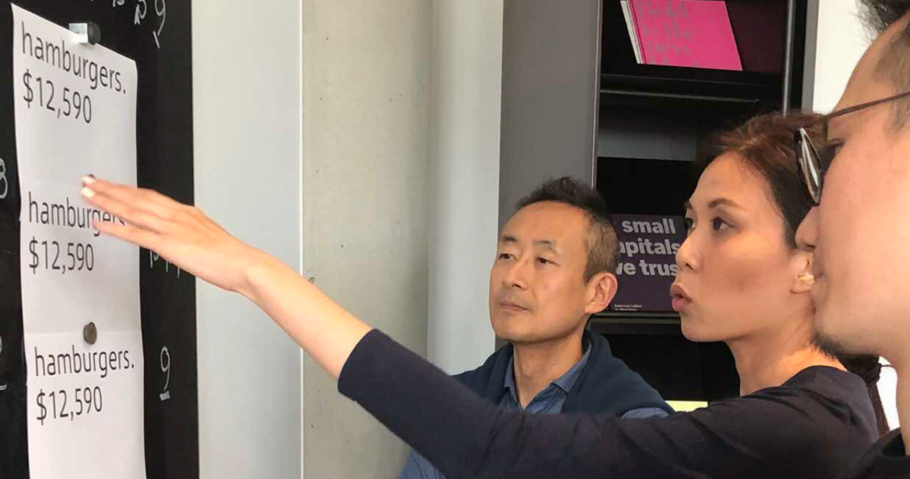
阿里巴巴集团的新字体赋能商家生态,让商业美而简单。
这套定制设计的 Alibaba Sans 字体家族将帮助其合作伙伴与客户提高品牌设计力。
挑战
阿里巴巴集团的企业品牌团队面临着各种设计挑战,因为在其创意团队、下属部门以及其庞大的数字合作伙伴和供应商生态系统中,一直使用着多个不同的开源字体。
随着业务快速增长,阿里巴巴越发需要一套统一、灵活、创新的字体家族,以保证设计师在能自由尝试的同时,又能严守品牌与知识产权规范。由于集团的核心业务是电商和零售,因此阿里巴巴字体不仅对字母有需求,对数字和货币符号的要求也极高。而更大的挑战是,阿里巴巴还希望在不断扩大的市场进行品牌营销活动时能轻松地与同事、合伙伴与客户分享这款品牌字体。
解决方案
Monotype 与阿里巴巴的设计团队成员通过真正的深层协作,组织了一系列为期多天的设计研讨会,聚焦于梳理新字体的设计理念,并讨论如何将阿里巴巴的企业个性融入其中。
Monotype 的设计团队由字体总监小林章先生领导。面对阿里巴巴集团的难题,他从绘制数字和货币符号入手,优先设计了电商业务最为重要的核心部分。团队从零开始,绘制数字和字母,创作出了 Alibaba Sans,其中还包括了造型独特的小写字母 a。这套字体不仅要赏心悦目,在粗字重下亦是如此;而且要能清晰易认,无论在各种设备和地点、无论字号大小——从横跨多栋写字楼的显示屏幕,到公司礼品店、零售商场以及各处电商网站。
为能准确抓住阿里巴巴内部员工自己所认同的公司形象,设计师们对集团的全球员工进行了问卷调查,根据结果确定了 “激情”、“力量”、“未来” 等关键词,制作出了 Alibaba Sans。这套定制字体将在 2019 年 4 月 27—28 日举行的 UCAN 设计大会上正式发布。通过设计的力量,公司获得了一套完备的系统字体,以保证能 “让商业美而简单”。
成果
对内成果:
• 提供了一套整合一致的品牌设计,各种业务均能轻松使用
• 利用这份高品质、多用途的知识产权进行探索试验、设计美观的营销活动
• 快速地将字体部署到各业务部门,促进合作,提高设计速度与投资回报
• 在各种设计接触点都能易于应用
对外成果:
• 以一套统一的品牌形象与企业特性进行沟通
• 在所有接触点让客户和合作伙伴辨清并使用新的品牌字体,消除市场认知的混乱状态
• 向所有公众免费提供新字体,强化品牌设计